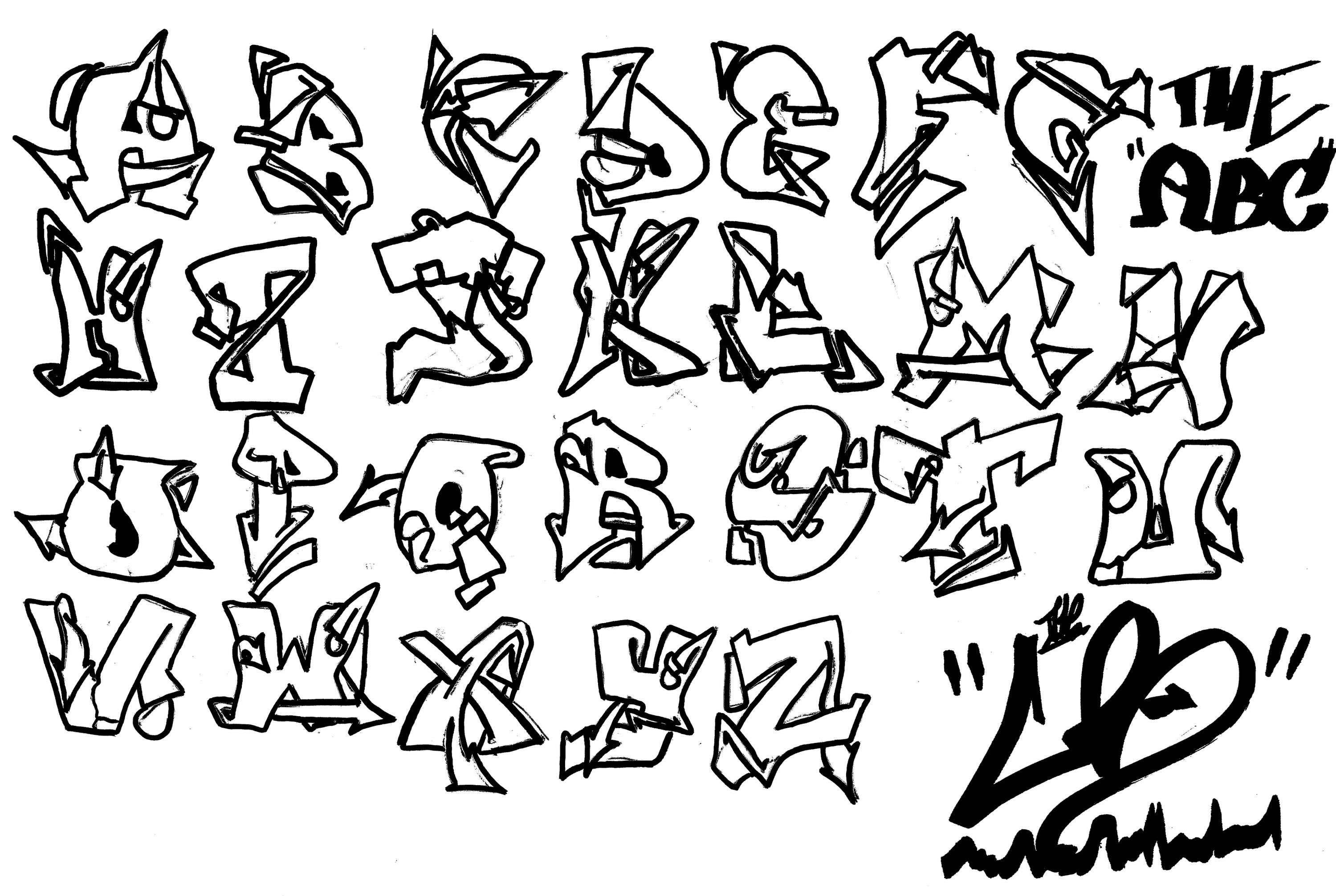
Шрифт Raslani Hip Hop , Рукописные — Граффити шрифты
От автора
16.
Please show me loveЗагрузите этот клёвый шрифт, чтобы добавить рукописное вдохновленние и чувства в Ваши работы. Изображение © Andrew Hart
Дизайнер Эндрю Харт — является автором Dirt 2, сайт, посвященный разнообразным ресурсам по дизайну, так же там можно загрузить шрифты. Есть много на выбор, но нам особенно понравился его рукописный шрифт в стиле записок под названием «Пожалуйста, покажи мне любовь». Примечание: бесплатная версия ограничена демонстрационным примером только в некоммерческих целях.
17. Hardkaze
Уникально названный именем дизайнера PizzaDude создал этот крутой шрифт в стиле граффити шрифтов Hardkaze.
Этот рисованной шрифт был разработан Джэйкобом Фишером aka Pizzadude. Основанный в Копенгагене, Фишер описывает свой стиль как «Свободный, спокойный и глупый», что особенно касается выражения с помощью уникальных шрифтов ручной работы.
18. Whoa
Этот крутой шрифт Whoa, был вдохновлен стилями граффити начала 90-ых
Если вы ищете шрифт граффити-стайл, который обладает мощностью, тогда проверяйте этот ‘Whoa’ шрифт.
Дизайнер комментирует свой сайт 11-D productions, «В детстве я часто был очарован всем хип-хоп граффити я видел вокруг в начале 90-х.. Школьная эпоха граффити была (и остается) очень увлекательно для меня «.
19. Ruthless One
Создавайте потрясающие граффити проекты с этим бриллиантом, Ruthless One шрифт. lllustration © Måns Grebäck
Другой шрифт от Måns Grebäck, мы не могли не включать этот бриллиант, Ruthless One дизайн. Дизайнер имеет почти 100 шрифтов и они доступны для скачивания бесплатно для личного пользования на Dafont.com, многие из них в граффити стиле.
28. Отряд бомбардировщиков
Представляем наш новый продукт под названием Bomber Squad Graffiti Font, вдохновленный стилем граффити с забавной темой, очень хорошо подходит для плакатов с граффити, музыки в стиле хип-хоп, детских плакатов, листовок, детской книги, мультфильмов, комиксов и т. Д.
29.Пузырьковая стрела
Bubble Boom вдохновлен граффити и хорошо подходит для таких тем, как плакаты с граффити, музыка в стиле хип-хоп, детские плакаты, листовки, детские книги, мультфильмы, комиксы и многое другое.